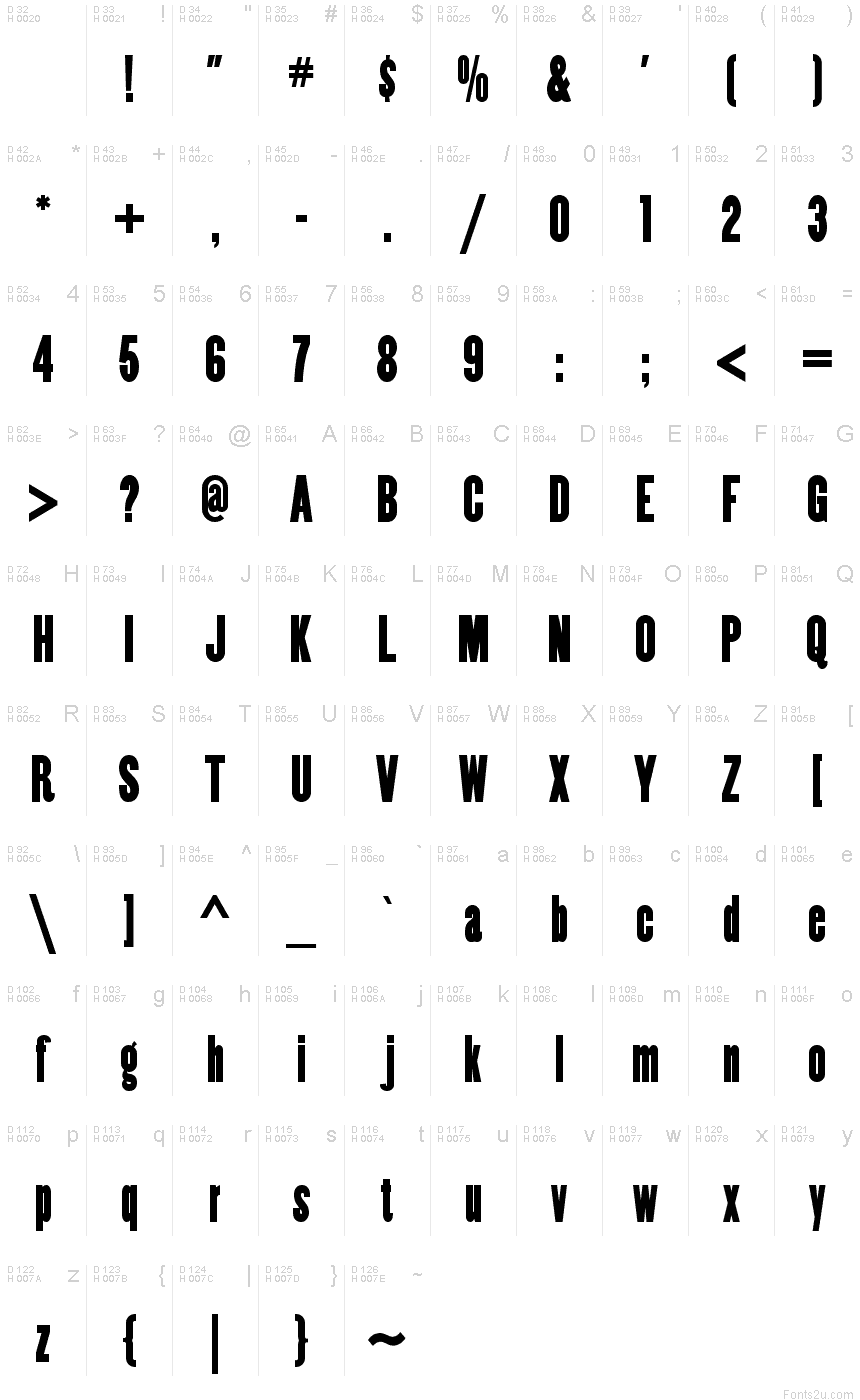
معاينة خط CopperCanyonWBW DemiBold
Copper Canyon WBW DemiBold من تصميم Nick Curtis هو خط مجاني بلا زوائد (sans serif) يحمل طابع ملصقات الطباعة الخشبية القديمة. تتميز عائلة Copper Canyon WBW بحروف ضيقة وطويلة، وخطوط عمودية سميكة، وزوايا مستديرة تمنح شعوراً بالحبر المنطبع بعمق في ورق خشن. إنه خط جريء يتمتع بلمسة من الخشونة، ويوحي فوراً بأجواء الروديو والسكك الحديدية والشوارع الترابية دون الوقوع في كليشيهات التصميم التقليدية.
باستخدام Copper Canyon WBW DemiBold، ستجذب العناوين الأنظار على ملصقات الفعاليات، لافتات الحانات، ملصقات المشروبات الحرفية، الشعارات القديمة (ريترو)، أغلفة الكتب، وتصاميم شبكات التواصل الاجتماعي. يتألق هذا الخط المجاني عند استخدامه بأحجام كبيرة، حيث تفرض أشكاله المضغوطة حضورها دون استهلاك مساحة أفقية كبيرة. بالنسبة للنص الأساسي، قم بدمجه مع خط بلا زوائد بسيط ومفتوح وبوزن أخف للحفاظ على وضوح الرسالة، بينما تترك لخط Copper Canyon WBW مهمة إبراز الهوية البصرية.